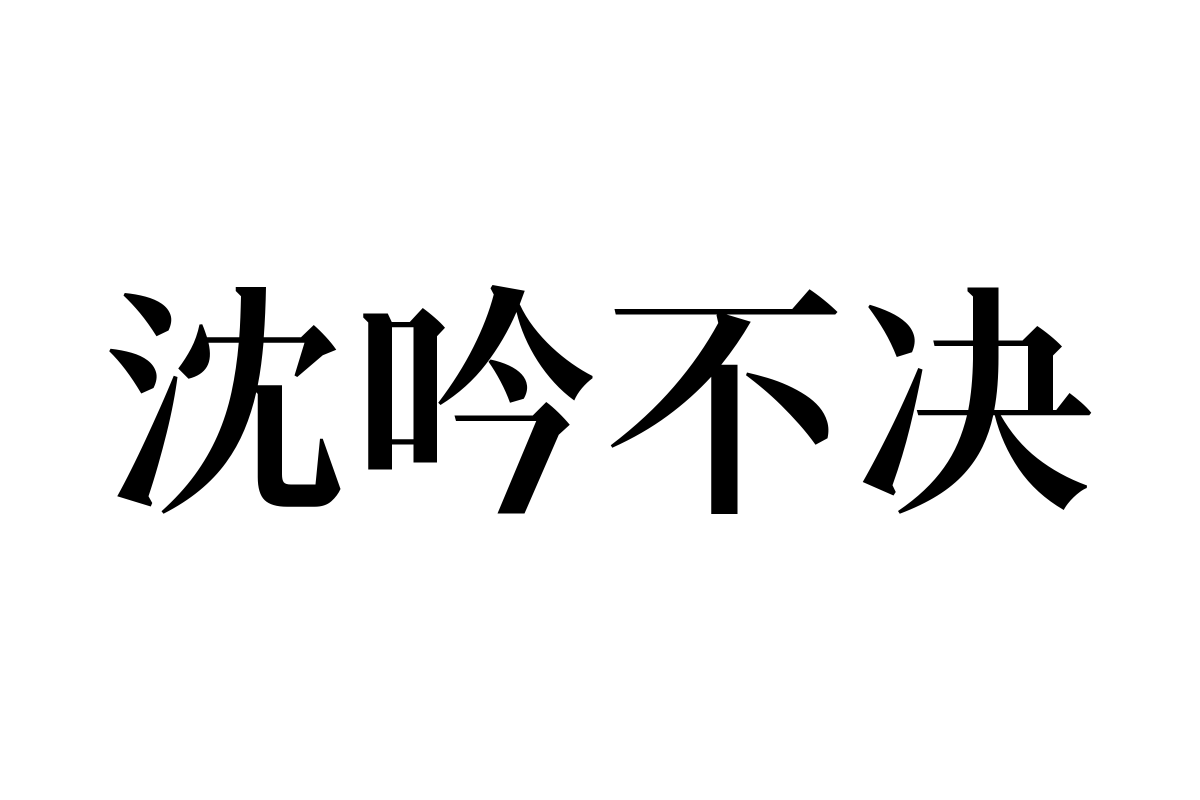
汉仪新人文宋65W是一款由汉仪公司开发的字体,具有独特的艺术风格和设计感。这款字体采用了宋体的基础结构,但在笔画的处理上进行了创新和优化,使其更加流畅、自然。同时,字体中的文字大小为65号,适合用于需要强调文字内容的场合。
该字体的设计风格独特,线条流畅而富有弹性,给人一种优雅而庄重的感觉。字体中的字形结构紧凑,但不失大气,适合用于各种正式场合的宣传材料、海报、广告等。此外,字体中的字符间距适中,不会过于拥挤或稀疏,能够保证文字的清晰度和可读性。
总的来说,汉仪新人文宋65W是一款非常适合用于商业宣传、文化传播等领域的字体。其独特的艺术风格和优秀的设计效果,能够为企业和个人提供更好的视觉体验和品牌形象。